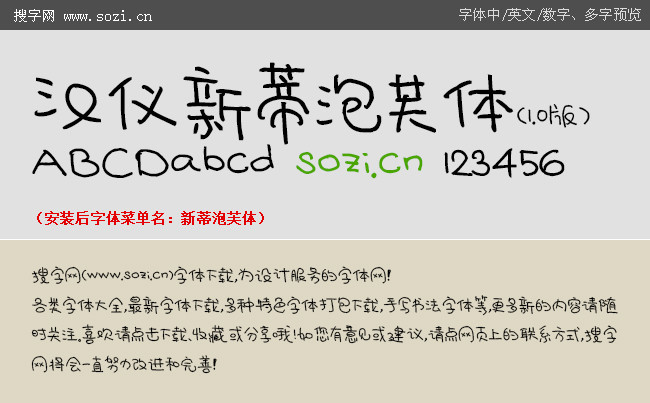
漢儀新蒂泡芙體1.0
搜字網(wǎng)提供一款漢儀新蒂泡芙體1.0字體下載,漢儀新蒂泡芙體是一款漂亮的手寫風(fēng)格藝術(shù)字體。由漢儀新蒂工作室出品,漢儀新蒂工作室成立于2016年,由漢儀字庫與新蒂字體聯(lián)合成立,本字體字形流暢大方,適合應(yīng)用于海報設(shè)計、藝術(shù)設(shè)計、包裝設(shè)計等應(yīng)用。(本字體為個人非商用版,如需要商用請聯(lián)系漢儀公司購買版權(quán))